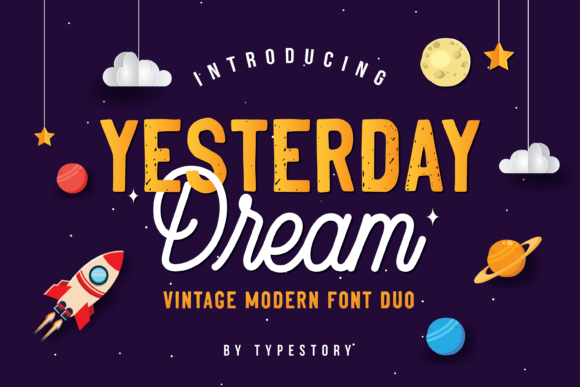
Yesterday Dream
قد يكون العثور على عناصر التصميم المناسبة أمرًا صعبًا، ولكن Yesterday Dream يقدم مجموعة استثنائية ترتقي بعملك على الفور.
سواء كنت تقوم بإنشاء منتجات الطباعة عند الطلب أو دعوات الزفاف أو رسومات وسائل التواصل الاجتماعي، فإن Yesterday Dream هو الخيار المثالي.